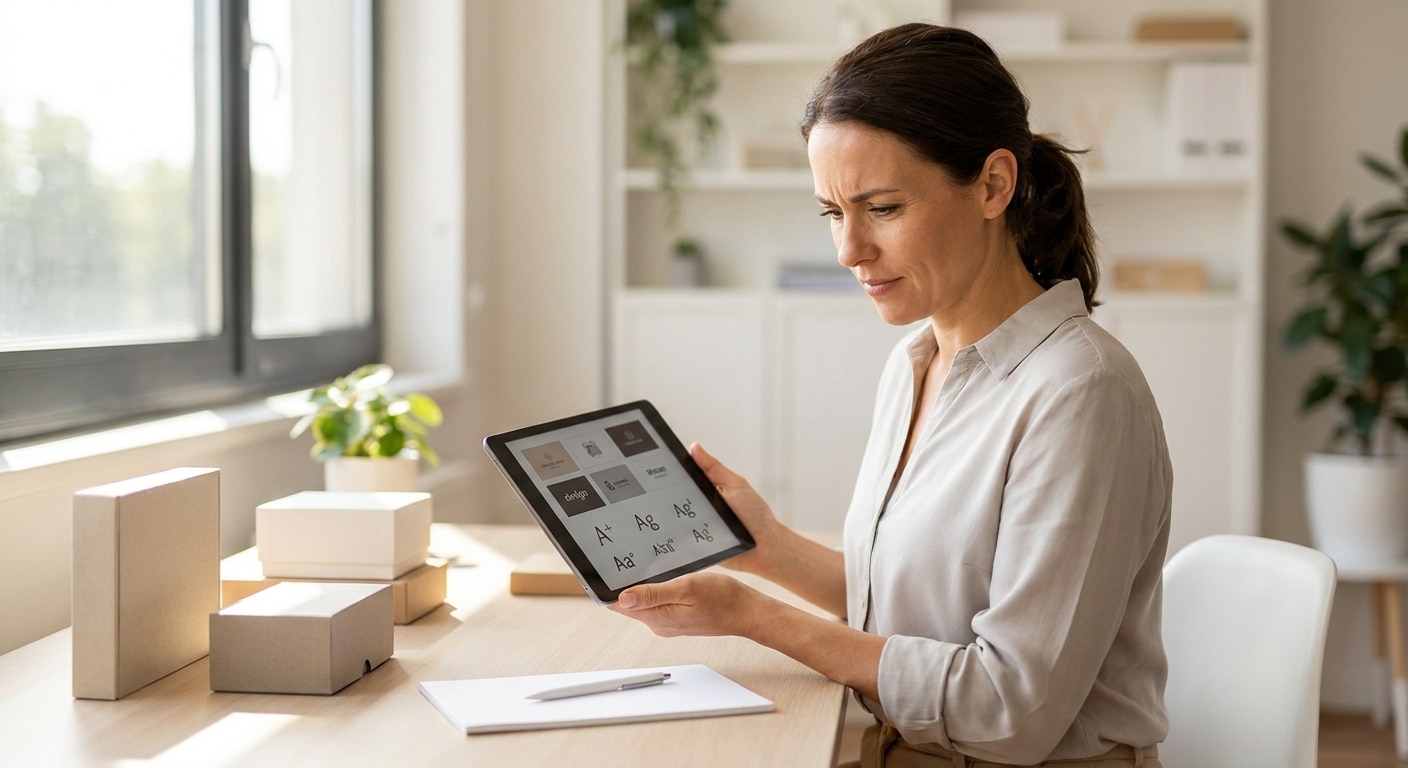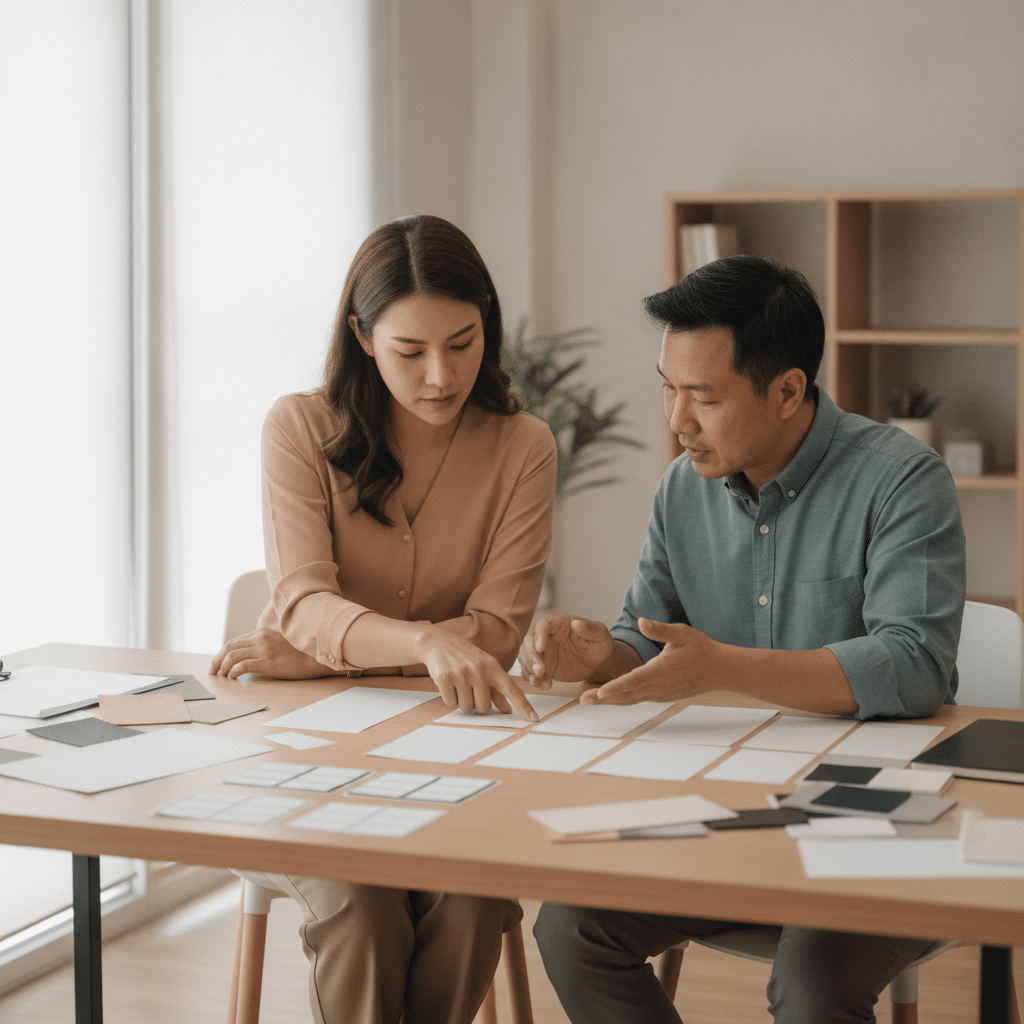
เลือกฟอนต์ทำป้าย-ฉลากสินค้าอย่างไร ให้ลูกค้าอ่านง่ายสะดุดตา
การเลือกรูปแบบตัวอักษร หรือ ฟอนต์ สำหรับการออกแบบป้ายโฆษณาและฉลากสินค้า ถือเป็นองค์ประกอบสำคัญที่มีผลต่อการรับรู้ของลูกค้าและความสำเร็จของแบรนด์โดยตรง ฟอนต์ที่ดีไม่เพียงแต่ทำหน้าที่สื่อสารข้อมูล แต่ยังสามารถสร้างเอกลักษณ์ สร้างความน่าเชื่อถือ และดึงดูดสายตาให้ผู้บริโภคตัดสินใจซื้อได้ในที่สุด
ประเด็นสำคัญที่น่าสนใจ
- ฟอนต์ที่เลือกใช้ต้องสะท้อนบุคลิกและคาแรคเตอร์ของสินค้าและแบรนด์ได้อย่างชัดเจน เพื่อสร้างการจดจำและสื่อสารกับกลุ่มเป้าหมายได้ตรงจุด
- จำกัดการใช้ฟอนต์บนฉลากหรือป้ายโฆษณาไม่เกิน 2-3 รูปแบบ เพื่อรักษาความเรียบง่าย เป็นระเบียบ และไม่สร้างความสับสนให้กับผู้อ่าน
- จัดลำดับความสำคัญของข้อมูลด้วยขนาดตัวอักษร โดยให้ชื่อสินค้ามีขนาดใหญ่ที่สุด ตามด้วยชื่อแบรนด์และรายละเอียด เพื่อนำทางสายตาของลูกค้า
- สีของตัวอักษรต้องมีความเปรียบต่าง (Contrast) กับสีพื้นหลังอย่างชัดเจน เพื่อให้สามารถอ่านได้ง่ายจากระยะไกลและในสภาพแสงที่แตกต่างกัน
หัวใจสำคัญของการเลือกฟอนต์ที่ไม่ควรมองข้าม
การเรียนรู้ว่าจะเลือกฟอนต์ทำป้าย-ฉลากสินค้าอย่างไร ให้ลูกค้าอ่านง่ายสะดุดตานั้น เป็นทักษะที่จำเป็นสำหรับผู้ประกอบการและนักออกแบบทุกคน เนื่องจากฟอนต์เปรียบเสมือน “เสียง” ของแบรนด์ที่สื่อสารกับลูกค้าโดยไม่ใช้คำพูด ตัวอักษรแต่ละรูปแบบสามารถกระตุ้นอารมณ์และความรู้สึกที่แตกต่างกันได้ ตั้งแต่ความหรูหรา น่าเชื่อถือ ความสนุกสนาน ไปจนถึงความเป็นธรรมชาติและเรียบง่าย การเลือกฟอนต์ที่เหมาะสมจึงเป็นการวางรากฐานสำคัญในการสร้างภาพลักษณ์ของผลิตภัณฑ์ให้เป็นที่จดจำและแตกต่างจากคู่แข่งในตลาด
ในโลกธุรกิจที่มีการแข่งขันสูง ลูกค้ามีเวลาเพียงไม่กี่วินาทีในการตัดสินใจเลือกซื้อสินค้าบนชั้นวาง ฉลากสินค้าและป้ายโฆษณาจึงเป็นด่านแรกที่จะต้องดึงดูดความสนใจและสื่อสารข้อมูลสำคัญให้ได้อย่างรวดเร็ว หากฟอนต์ที่ใช้อ่านยาก มีความซับซ้อน หรือไม่เข้ากับตัวตนของสินค้า ก็อาจทำให้ลูกค้ามองข้ามไปอย่างน่าเสียดาย ดังนั้น การทำความเข้าใจในหลักการเลือกและใช้งานฟอนต์จึงไม่ใช่แค่เรื่องของความสวยงาม แต่เป็นกลยุทธ์ทางการตลาดที่ส่งผลโดยตรงต่อการรับรู้และยอดขายของแบรนด์
“ในเชิงธุรกิจ หากลูกค้าไม่สามารถอ่านและทำความเข้าใจข้อความบนป้ายหรือฉลากสินค้าได้ภายใน 3 วินาทีแรก โอกาสในการขายสินค้านั้นอาจหลุดลอยไปทันที”
ดังนั้น ผู้ประกอบการธุรกิจ SME และเจ้าของแบรนด์จึงควรให้ความสำคัญกับการเลือกฟอนต์เทียบเท่ากับการพัฒนาคุณภาพของสินค้า เพราะมันคือเครื่องมือสื่อสารที่ทรงพลังซึ่งสามารถสร้างความประทับใจแรกและนำไปสู่การเป็นลูกค้าในระยะยาวได้
หลักการพื้นฐานในการเลือกฟอนต์สำหรับงานพิมพ์
การเลือกฟอนต์ที่มีประสิทธิภาพต้องอาศัยทั้งศาสตร์และศิลป์ โดยต้องคำนึงถึงปัจจัยหลายอย่างประกอบกัน ตั้งแต่บุคลิกของแบรนด์ไปจนถึงความสามารถในการอ่านของตัวอักษร หลักการพื้นฐานต่อไปนี้จะช่วยเป็นแนวทางในการตัดสินใจเลือกฟอนต์ให้เหมาะสมกับงานพิมพ์ทุกประเภท
เลือกรูปแบบฟอนต์ให้สะท้อนตัวตนของแบรนด์
ก่อนจะตัดสินใจเลือกฟอนต์ใดๆ สิ่งสำคัญคือการทำความเข้าใจ “คาแรคเตอร์” ของสินค้าและแบรนด์ให้ถ่องแท้เสียก่อน สินค้าของคุณมีภาพลักษณ์แบบใด: หรูหรา, ทันสมัย, เป็นมิตร, ออร์แกนิก, หรือเหมาะสำหรับเด็ก? คำตอบของคำถามนี้จะเป็นตัวกำหนดทิศทางในการเลือกฟอนต์
- ความเรียบง่ายคือหัวใจ (Simplicity is Key): ในปัจจุบัน ฟอนต์ที่มีความสะอาดตา เรียบง่าย และไม่ซับซ้อนมักจะได้รับความนิยมสูง เนื่องจากทำให้สินค้าดูทันสมัย ไม่ตกยุคง่าย และช่วยให้ผู้บริโภคจดจำชื่อแบรนด์และสินค้าได้ง่ายขึ้น ฟอนต์ที่เรียบง่ายยังมีความยืดหยุ่นในการนำไปปรับใช้กับสื่อต่างๆ ได้ดีกว่า
- จับคู่ตามคาแรคเตอร์ (Match the Character): ฟอนต์แต่ละตระกูลมีบุคลิกที่แตกต่างกันอย่างชัดเจน ตัวอย่างเช่น ฟอนต์มีเชิง (Serif) ที่มีขีดเล็กๆ ที่ปลายตัวอักษร มักให้ความรู้สึกคลาสสิก เป็นทางการ และน่าเชื่อถือ เหมาะสำหรับสินค้าที่ต้องการสร้างภาพลักษณ์หรูหราหรือแบรนด์ที่มีประวัติยาวนาน ในขณะที่ฟอนต์ไม่มีเชิง (Sans-serif) ที่ไม่มีขีดดังกล่าว จะให้ความรู้สึกทันสมัย เรียบง่าย และเข้าถึงง่าย เหมาะสำหรับสินค้าเทคโนโลยี สตาร์ทอัพ หรือแบรนด์ที่ต้องการสื่อสารความเป็นมิตร
สูตรการจับคู่ฟอนต์อย่างมืออาชีพ
การใช้ฟอนต์มากกว่าหนึ่งแบบบนฉลากสินค้าเป็นเทคนิคที่ช่วยสร้างมิติและความน่าสนใจได้ แต่ต้องทำอย่างมีหลักการเพื่อไม่ให้ดูรกตา สูตรที่นักออกแบบนิยมใช้และได้ผลดีเสมอคือการจับคู่ระหว่างฟอนต์ต่างตระกูลกัน
- หัวข้อ (Header): สำหรับชื่อสินค้าหรือข้อความที่ต้องการดึงดูดสายตาจากระยะไกล ควรใช้ฟอนต์ไม่มีเชิง (Sans-serif) ที่มีความหนา (Bold) เพื่อให้โดดเด่นและอ่านง่ายที่สุด
- เนื้อหารายละเอียด (Body): สำหรับข้อมูลส่วนผสม วิธีใช้ หรือคำอธิบายเพิ่มเติม ควรใช้ฟอนต์มีเชิง (Serif) ที่มีความบาง (Light/Regular) เนื่องจากเชิงของตัวอักษรจะช่วยนำทางสายตา ทำให้อ่านข้อความยาวๆ ได้สบายตามากขึ้น และยังช่วยเสริมให้สินค้าดูมีราคาและมีระดับมากขึ้นอีกด้วย
| ประเภทฟอนต์ | ลักษณะเด่น | ความรู้สึกที่สื่อ | เหมาะสำหรับ |
|---|---|---|---|
| ฟอนต์ไม่มีเชิง (Sans-serif) | ตัวอักษรไม่มีขีดที่ปลาย, เรียบง่าย, สะอาดตา | ทันสมัย, เป็นมิตร, เข้าถึงง่าย, ชัดเจน | หัวข้อหลัก, ชื่อสินค้า, ป้ายโฆษณา, แบรนด์เทคโนโลยี |
| ฟอนต์มีเชิง (Serif) | ตัวอักษรมีขีดเล็กๆ ที่ปลาย, มีความต่างของเส้นหนาบาง | คลาสสิก, น่าเชื่อถือ, เป็นทางการ, หรูหรา | เนื้อหารายละเอียด, บทความยาวๆ, แบรนด์ที่เน้นประวัติศาสตร์และความน่าเชื่อถือ |
เทคนิคการจัดวางองค์ประกอบฟอนต์เพื่อประสิทธิภาพสูงสุด
นอกจากการเลือกรูปแบบฟอนต์ที่เหมาะสมแล้ว การจัดวางตัวอักษรบนพื้นที่ของฉลากหรือป้ายก็มีความสำคัญไม่แพ้กัน การจัดวางที่ดีจะช่วยให้ข้อมูลเป็นระเบียบ อ่านง่าย และดึงดูดสายตาได้อย่างมีประสิทธิภาพ